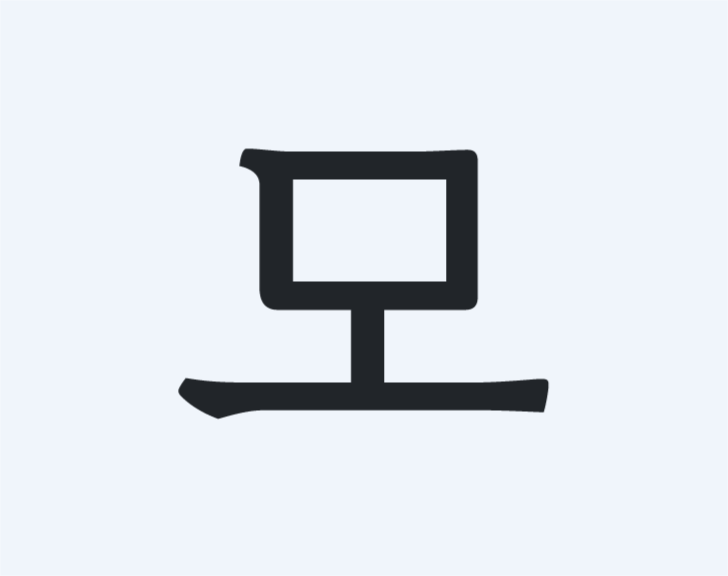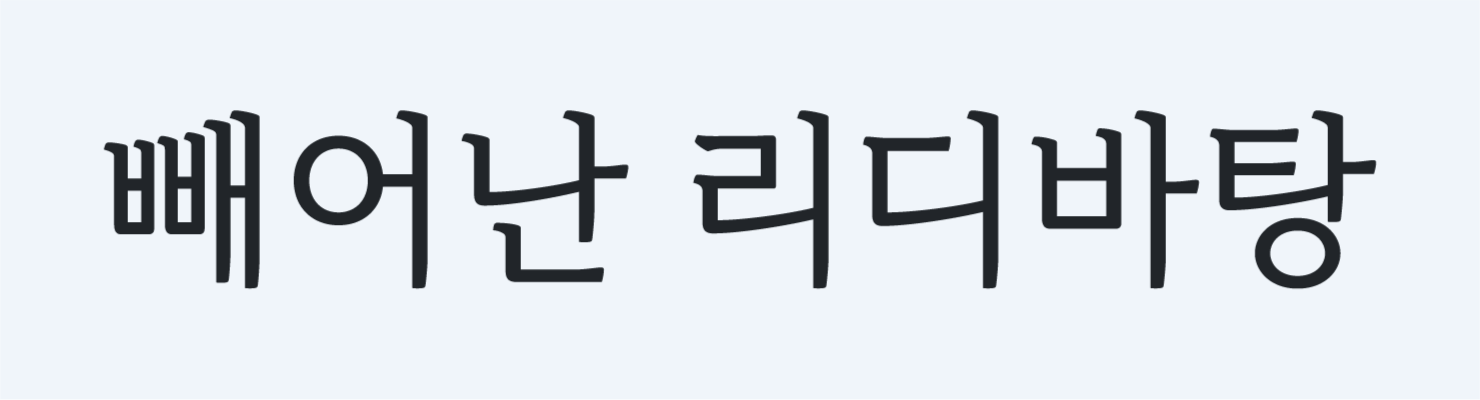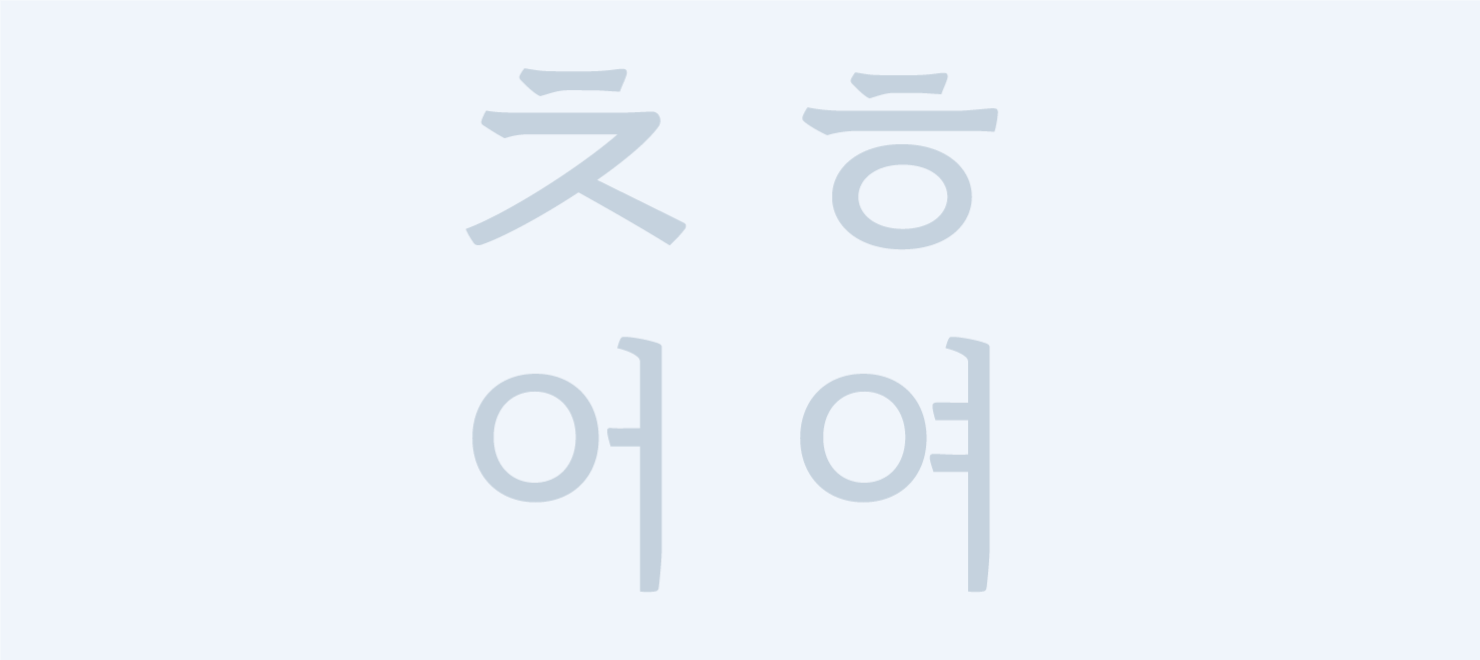
전자책을 비롯해서 웹툰, 만화, 웹소설 등을 제공하는 리디(주)에서 전자책 전용 폰트로 제작한 리디바탕체를 무료로 다운로드하는 방법을 살펴본다. 더불어 누구나 무료로 사용이 가능한 리디바탕체를 설치하는 방법과 코딩 시에 사용하는 방법도 살펴본다.
위의 이미지에서 보듯이 리디바탕체는 전자책에 최적화한 전용 글꼴로 또렷하게 읽히는 가독성을 목적으로 제작한 폰트이다. 즉, 리디바탕체는 e-ink 기기 즉 이북과 같은 전자책과 모바일 플랫폼에서 독서용으로 적합한 폰트이다.
해당 리디바탕체는 단일 글꼴인 1종으로 제작되었는데, 한글 11,172자를 비롯해서 라틴 94자 그리고 약물 984자로 구성되어 있다. 더불어 가독성을 높이는 글꼴 디자인면에 중심을 둔 폰트이다 보니 널리 알려진 ttf 포맷이 아닌 otf 포맷으로만 제공하고 있다.